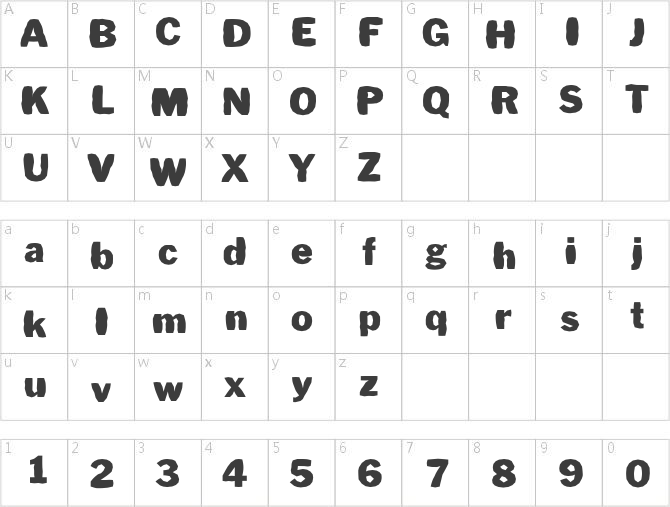
FZ BASIC 56 MANGLED 詳情頁
FZ BASIC 56 MANGLED
FZ BASIC 56 MANGLED介紹
FZ BASIC 56 MANGLED字體字庫是一款讓人賞心悅目、百看不厭的英文字體,適合各類廣告和產品包裝設計應用,字體大小0.07MB,格式為ttf字體,上傳用戶是小李哥/,作者/版權方為未知